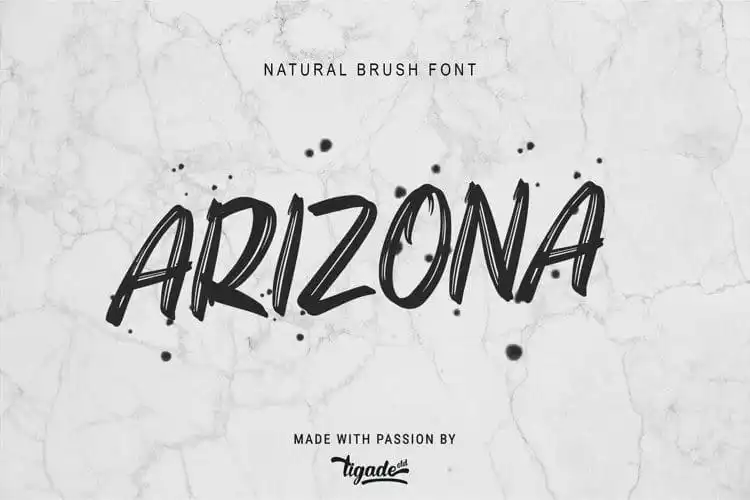
Arizona Brush Font é uma fonte de traço criada para aqueles que buscam estilo único e versatilidade na escrita de textos digitais. Inspirada no desenho artístico, essa fonte apresenta um contraste atraente entre as versões sólidas e borradas, além de linhas de base não regulares para cada caractere. Atualmente, ela oferece apenas letras maiúsculas com uma limitação de pontuação, mas o designer já anunciou planos para atualizações futuras que incluirão letras minúsculas e outras variações alternativas. Sem dúvida, é uma fonte ideal para aqueles buscando um touch de originalidade em seus projetos gráficos, seja em anúncios digitais ou textos de publicações online.